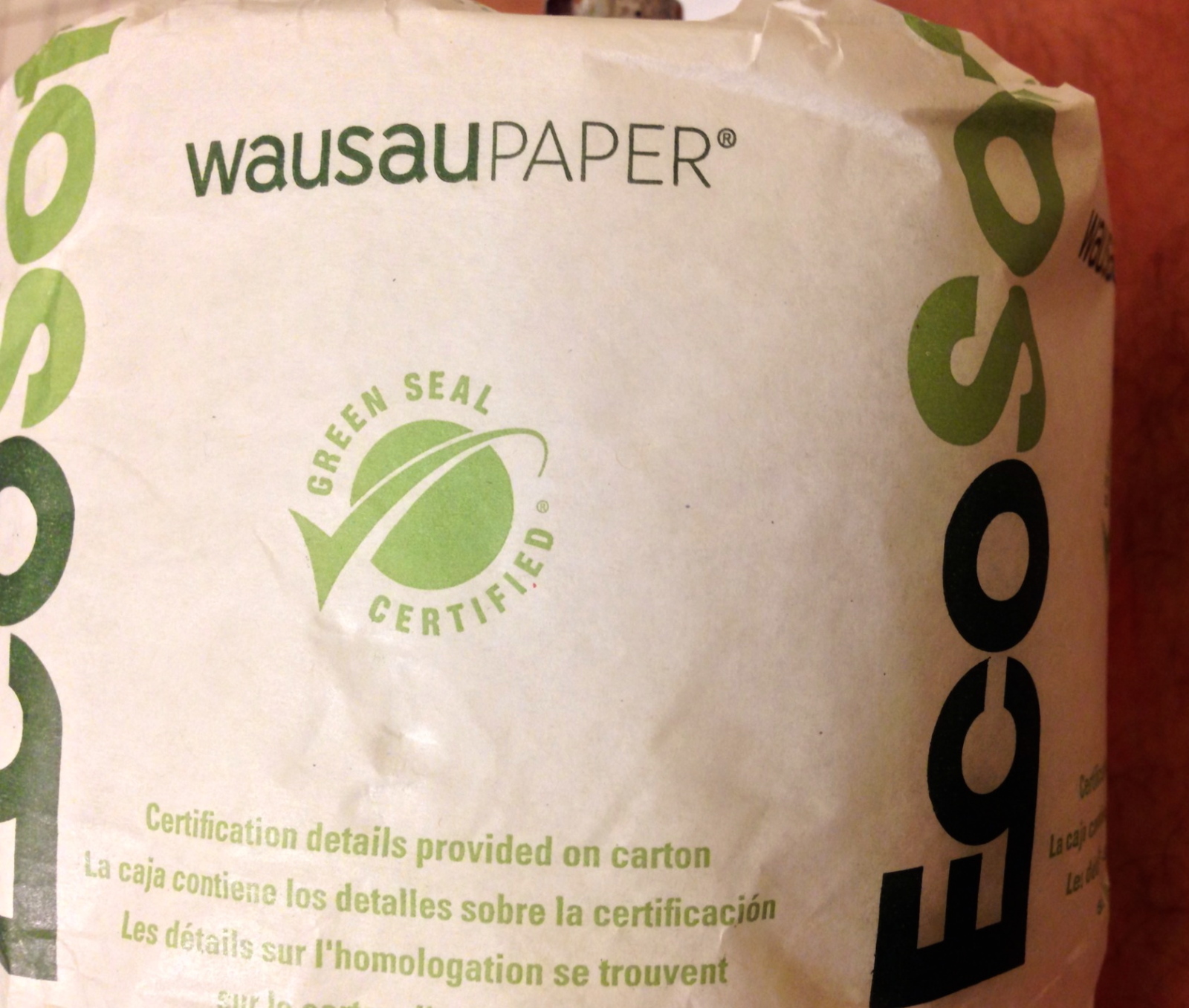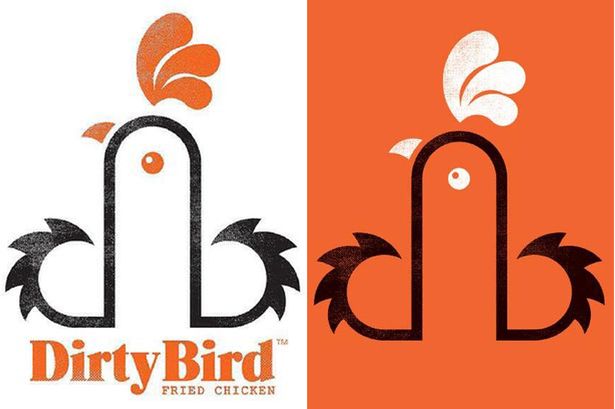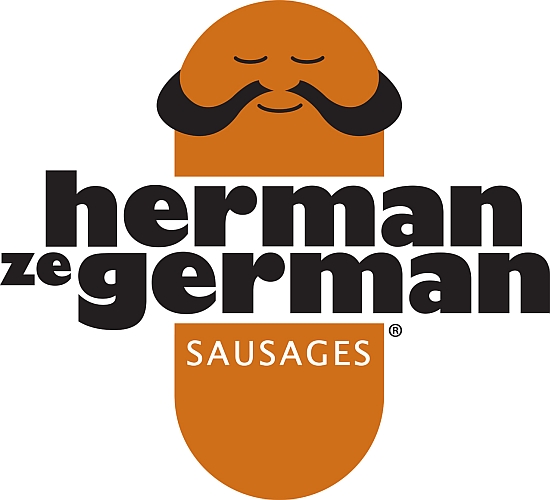
Das Schwungverbot bei uns in der Agentur wurde 1998 oder 99 ausgerufen – war »eierdidi« etwa trotzdem früher dran?
im deutschen sprachraum wäre diese marke möglicherweise wie geschaffen für's sohlenklebende hundegeschäft und so weiter. hier in einem hotel im us-amerikanischen portland (or) ist es die ersatzklorolle im bad.
We’ve never really thought about it like that. Our designer created a d and b for “dirty bird” then pushed them together to make a cockerel
“cockerel„? Genau das hat der Designer dann ja wohl gleich doppelt geschafft :-)
Junior Jazz Dance dagegen finde ich im optischen Täuschungs-Zusammenhang richtig klasse, passt so in dieses Täuschungs-Schema wie die Bilder Alte Frau vs. Junges Mädchen oder Ente vs. Hase
Our designer created a d and b for “dirty bird” then pushed them together
ha! darauf wäre ich als letztes gekommen.
bei dem junior jazz dance habe ich auch 'ne weil gebraucht aber jetzt sehe ich nur noch sasha grey. :D
Das ist wirklich ein echtes Logo??  :party:
Und bestimmt so gewollt. Der Laden heißt doch nicht umsonst Dirty Chicken. Ist alles Teil des Gesamtkonzepts, incl. der Erklärung für prüde Hühnenesser. Alles in allem ein geniales CI-Konzept, würde ich mal sagen. Vor einem Reporter tun ein paar „anständige“ Leute natürlich so, als würden sie sich genieren – aber dann essen sie trotzdem dort und erinnern sich immer an diesem Hühnchenfrittierer wie keinen zweiten.
Alles andere als missglückt. Jetzt kennt diese Marke die ganze Welt. Hätten die ein 08/15 Bravlogo hätten wir das nie erfahren, und nicht ausgeschlossen, dass daraus noch eine weltweite Francising-Hänchen (ach nein Cockchen) Kette wird...